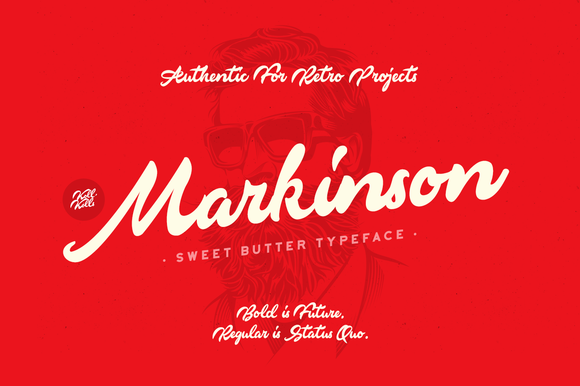
Markinson Script Font – Download Grátis
Markinson é uma nova tipografia script com estilo de escrita a mão. Este tipo especializado em traços finos apresenta detalhes exuberantes que remetem ao charme dos textos elaborados a olho nu. Easetype, o designer responsável por Markinson Script Font, investiu tempo e atenção na criação desse belo texto à mão livre, resultando em um ícone perfeito para criar mensagens fortes e impactantes. Seja para nomes de marca, cartazes de eventos ou qualquer projeto que precise de uma escrita elegante e atraente, Markinson é sua escolha ideal. Sua rica textura e personalidade garantirão um resultado memorável, tornando este tipo fonte uma perfeita adição ao seu arsenal criativo.